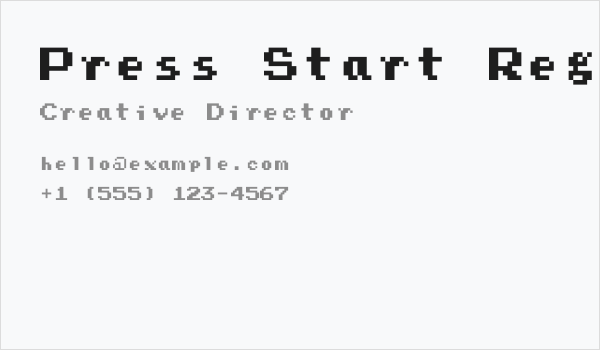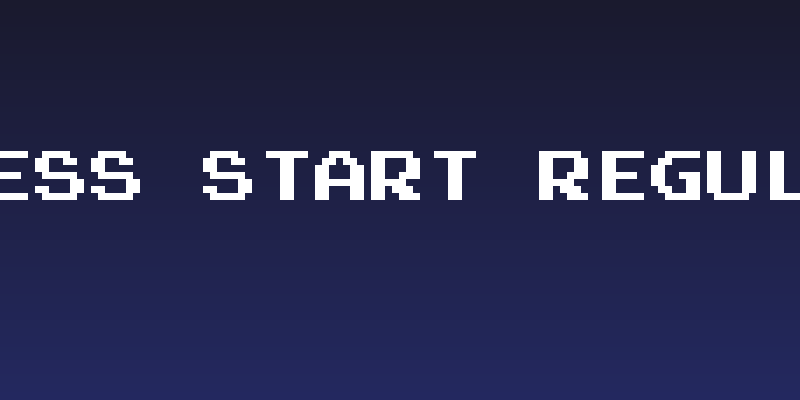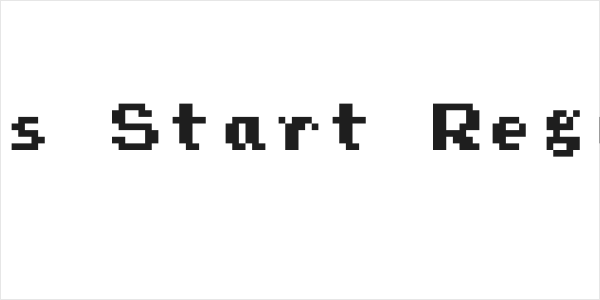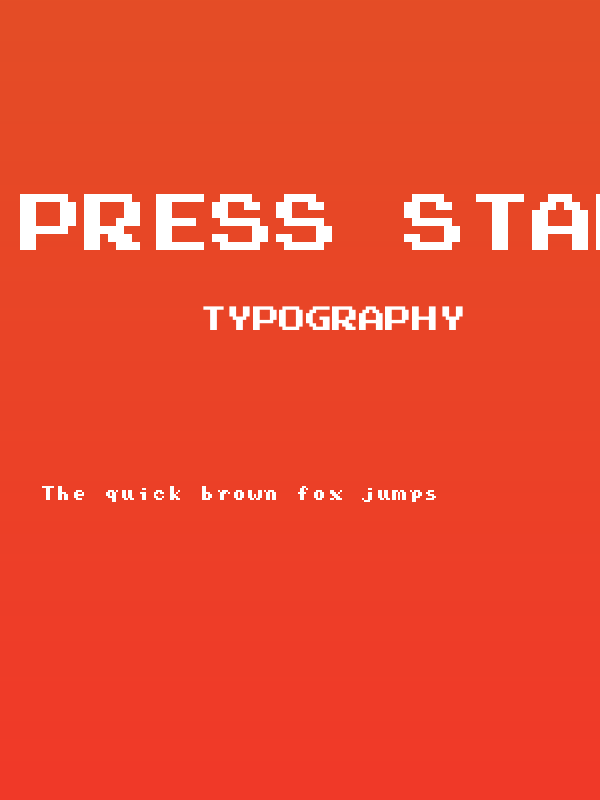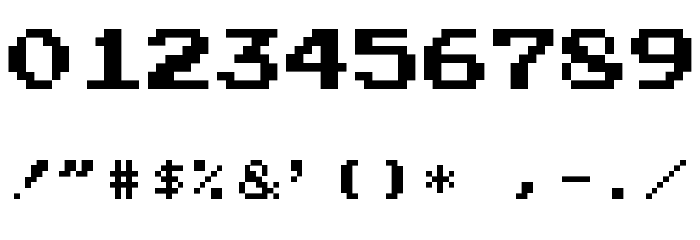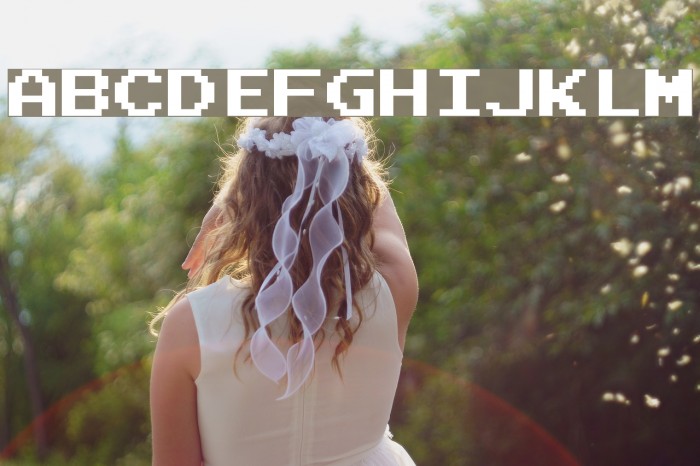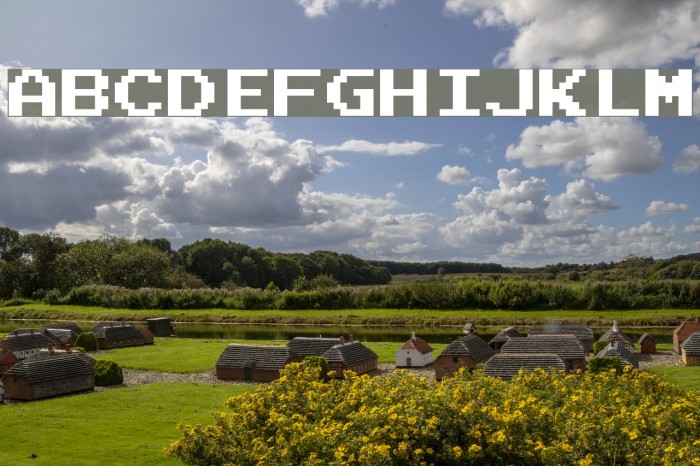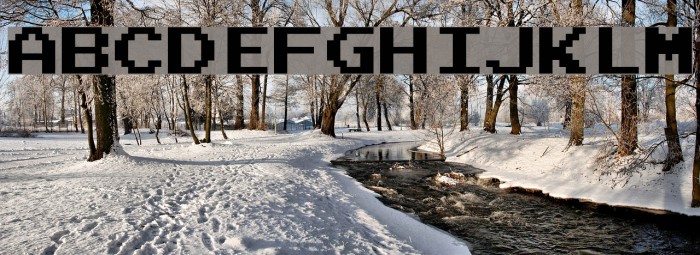
Press Start Regular Font
| Estilo general | Vintage |
| Caso de uso | Logos, Headlines, Digital Art |
| Proyectos propuestos | Ideal for video game designs, retro-themed posters, digital art projects, and any creative work that seeks to capture a nostalgic, 8-bit aesthetic. |